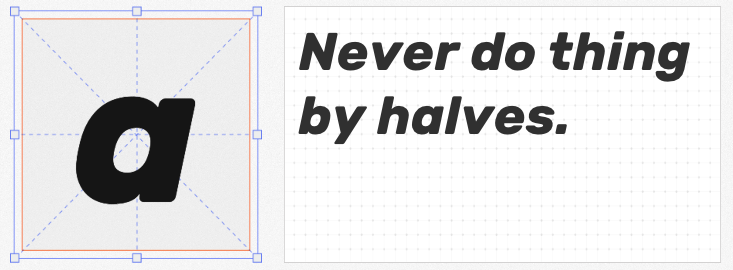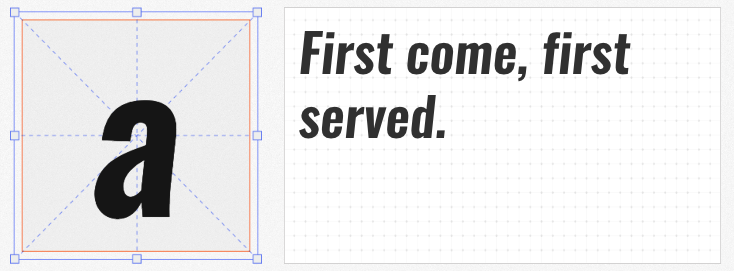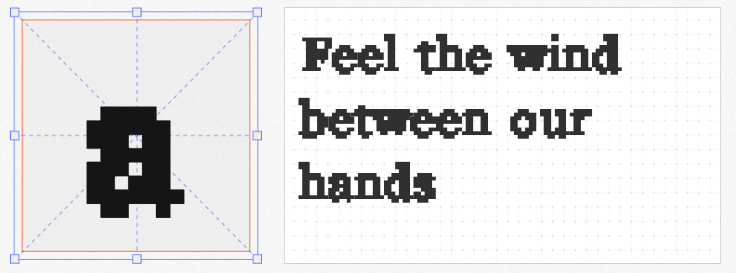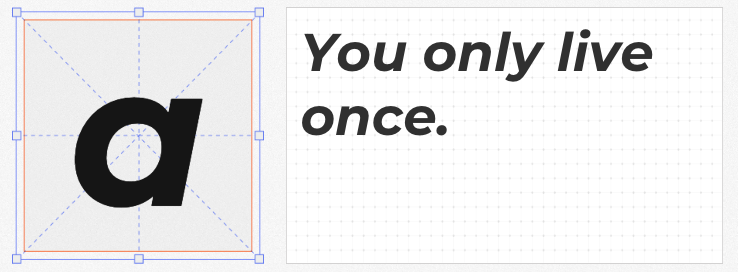
在商业设计项目中,选择兼具美观与实用性的免费英文字体至关重要。本文精选四款开源且可免费商用的英文字体,涵盖现代简约、复古改造、海岛风情与像素艺术四大风格,助力设计师高效完成作品。
1. Rubik Bold Italic
作为开源字体家族的代表,Rubik由专业设计师精心打造,以现代无衬线风格为核心,兼顾易读性与视觉冲击力。其斜体版本(Bold Italic)通过倾斜角度与笔画粗细的精准控制,在动态感与稳定性间找到完美平衡,尤其适合科技、教育类项目的标题与重点信息呈现。丰富的字重变化(从Light到Black)更支持多场景灵活应用。
2. Oswald DemiBoldItalic
Oswald DdemiBoldItalic是对经典“交替哥特式”字体的数字化重生。设计师通过重新绘制笔画轮廓,使其完美适配数字屏幕的像素网格,DemiBoldItalic版本在保留复古韵味的同时,强化了斜体的优雅曲线。这款字体特别适合需要传递历史感与现代感交织的品牌视觉,如文化展览、复古风品牌包装等。
3. Montserrat Bold Italic
灵感源自蒙特塞拉特岛的建筑与自然景观,Montserrat以简洁的几何线条构建字体骨架,Bold Italic版本通过倾斜角度赋予其流动感,仿佛海风拂过岩石。其独特的“海岛气质”使其成为旅游、生活方式类设计的首选,无论是海报标题还是品牌标语,都能瞬间传递轻松惬意的氛围。
4. 珊瑚 ENG
突破传统字体设计框架,珊瑚 ENG以显示器子像素渲染为灵感,通过彩色方点组合形成字母。这种像素风格不仅还原了早期数字设备的视觉语言,更以低多边形(Low Poly)美学契合当下潮流。适用于科技产品界面、游戏设计或需要强调数字原生感的创意项目,为作品注入赛博朋克式的未来气息。